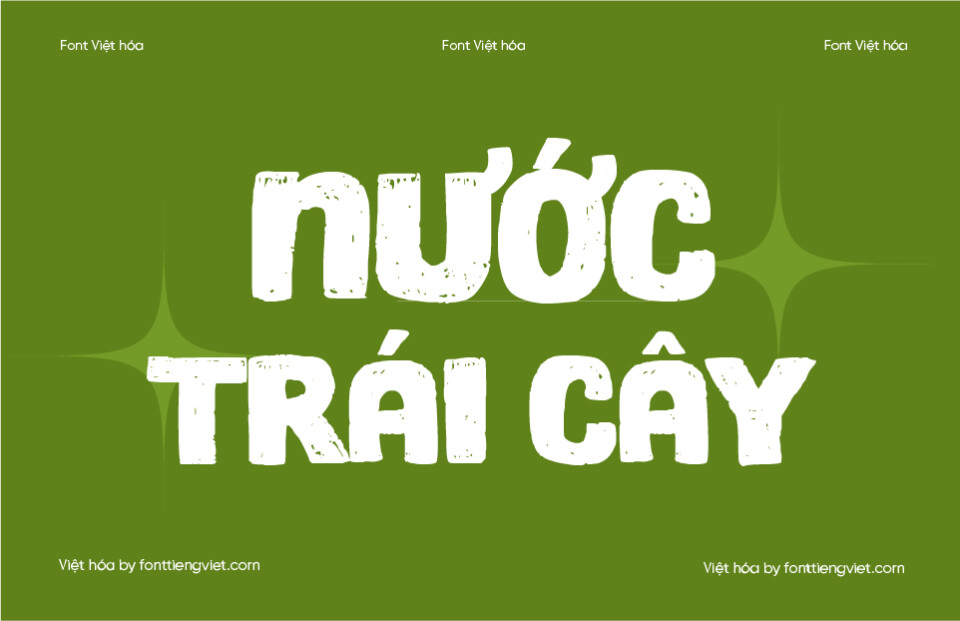
Trong thế giới thiết kế đồ họa hiện đại, việc lựa chọn một bộ Font Chữ phù hợp đóng vai trò quyết định đến sự thành công của một tác phẩm nghệ thuật. Font Việt hóa 1FTV VIP Super Pulp là một trong những lựa chọn hàng đầu cho các nhà thiết kế đang tìm kiếm sự phá cách và ấn tượng. Được lấy cảm hứng từ phong cách retro và các bìa truyện tranh cổ điển, bộ font này mang đến một luồng gió mới, đầy năng lượng và sức sống cho mọi dự án từ in ấn đến kỹ thuật số.
Khám phá đặc điểm nổi bật của Font Việt hóa 1FTV VIP Super Pulp
Phong cách thiết kế độc đáo và mạnh mẽ
Font Việt hóa 1FTV VIP Super Pulp nổi bật với những đường nét dày, đậm và có phần thô ráp tự nhiên. Điều này giúp bộ chữ tạo ra hiệu ứng thị giác mạnh mẽ, ngay lập tức thu hút sự chú ý của người xem. Đặc biệt, phiên bản Việt hóa đã được tinh chỉnh kỹ lưỡng các dấu câu để đảm bảo tính thẩm mỹ cao nhất khi sử dụng tiếng Việt. Các ký tự được thiết kế với độ tương phản cao, giúp cho tiêu đề của bạn trở nên nổi bật hơn bao giờ hết trên mọi nền màu sắc khác nhau.
Tính ứng dụng linh hoạt trong giáo dục và đời sống
Đối với các bạn học sinh và giáo viên, việc sử dụng font chữ này trong các bài thuyết trình hay thiết kế báo tường sẽ giúp nội dung trở nên sinh động và lôi cuốn hơn. Font Việt hóa 1FTV VIP Super Pulp cực kỳ phù hợp cho các chủ đề về thể thao, sự kiện năng động hoặc các dự án mang tính chất hoài cổ. Bạn có thể sử dụng font này để làm logo, banner quảng cáo hoặc bìa sách mà không lo lắng về vấn đề lỗi hiển thị ngôn ngữ.